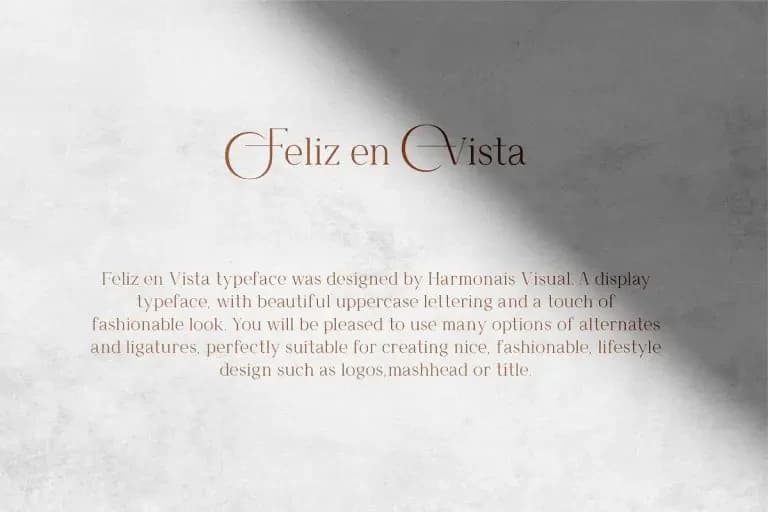
Feliz en Vista Display Font Örneği
Feliz en Vista Display Font – modern bir serif, gösterim yazı tipi; güzel büyük harflerle ve modaya uygun bir görünüm dokunuşuyla. Alternatifler ve ligatür seçeneklerini kullanmaktan memnun kalacaksınız; logolar, masthead, başlık ve düğün davetiyesi kağıdı gibi şık, moda odaklı yaşam tarzı tasarımları oluşturmak için mükemmel şekilde uygundur.